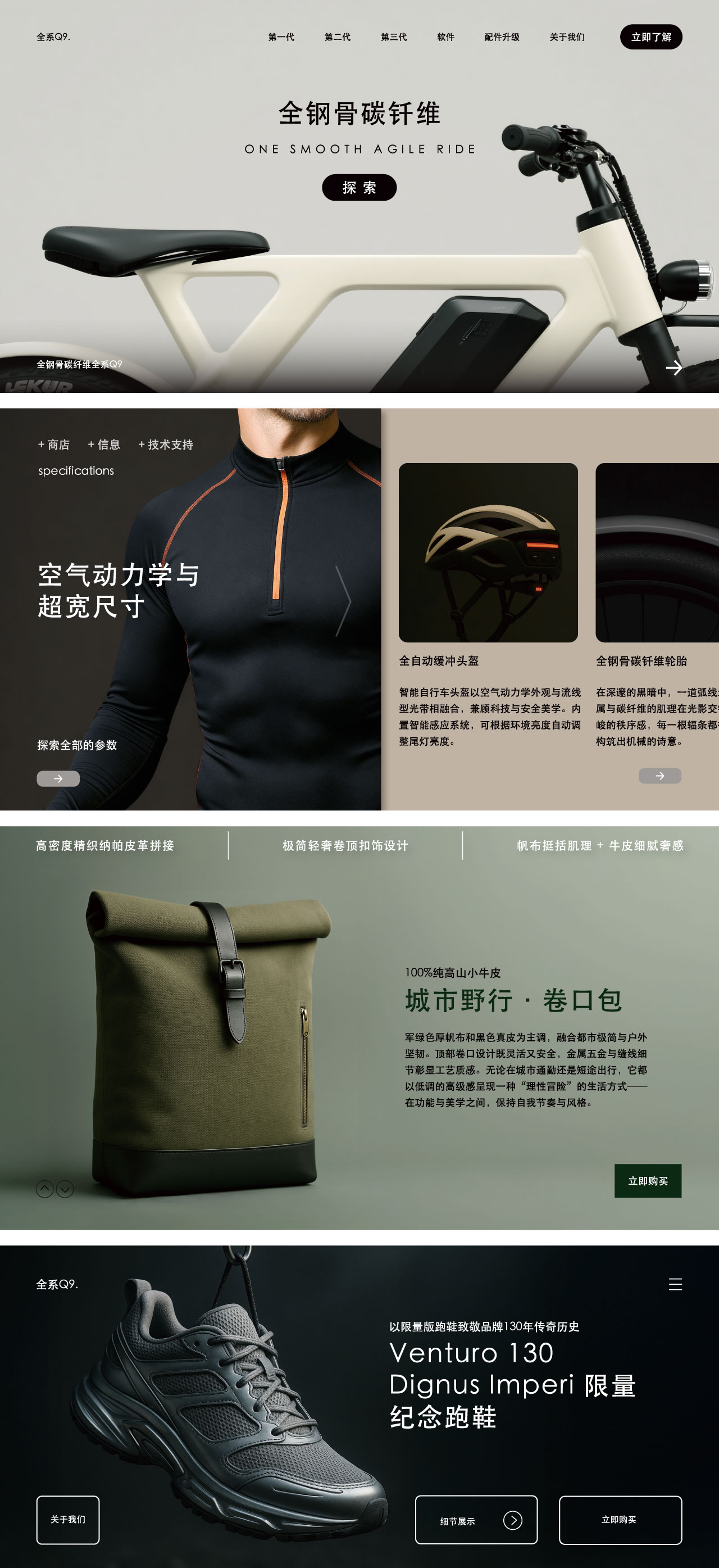
华文黑体 / STHeiti / Regular
华文黑体
在有限的空间进行无限分割
华文黑体 / STHeiti
设计师:
常州华文
字体介绍:
华文黑体字体是一款非常端正的中文字体,大方得体,华文黑体承袭了国家於六十年代、委托上海印刷研究所和字模厂的老师傅设计的黑一体、黑二体的模样,字体受传统中国书法美学的影响,结构外弛内张,构成的字体感觉传统儒雅,而且充满人性,比起新派设计-负空间讲究平均分布的,在以汉字为主的文字上可读性要胜一筹。